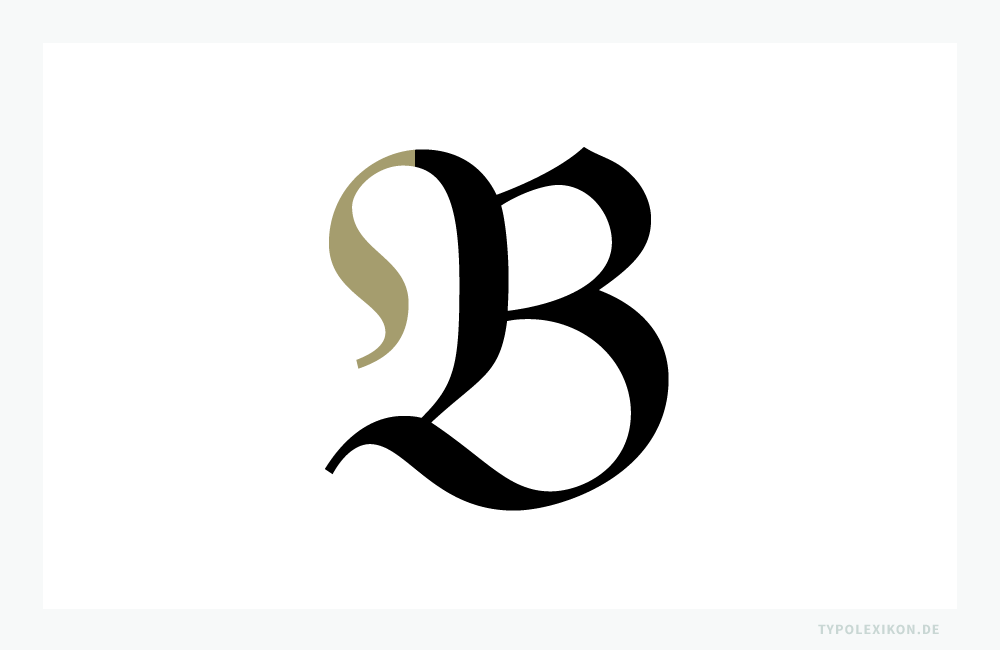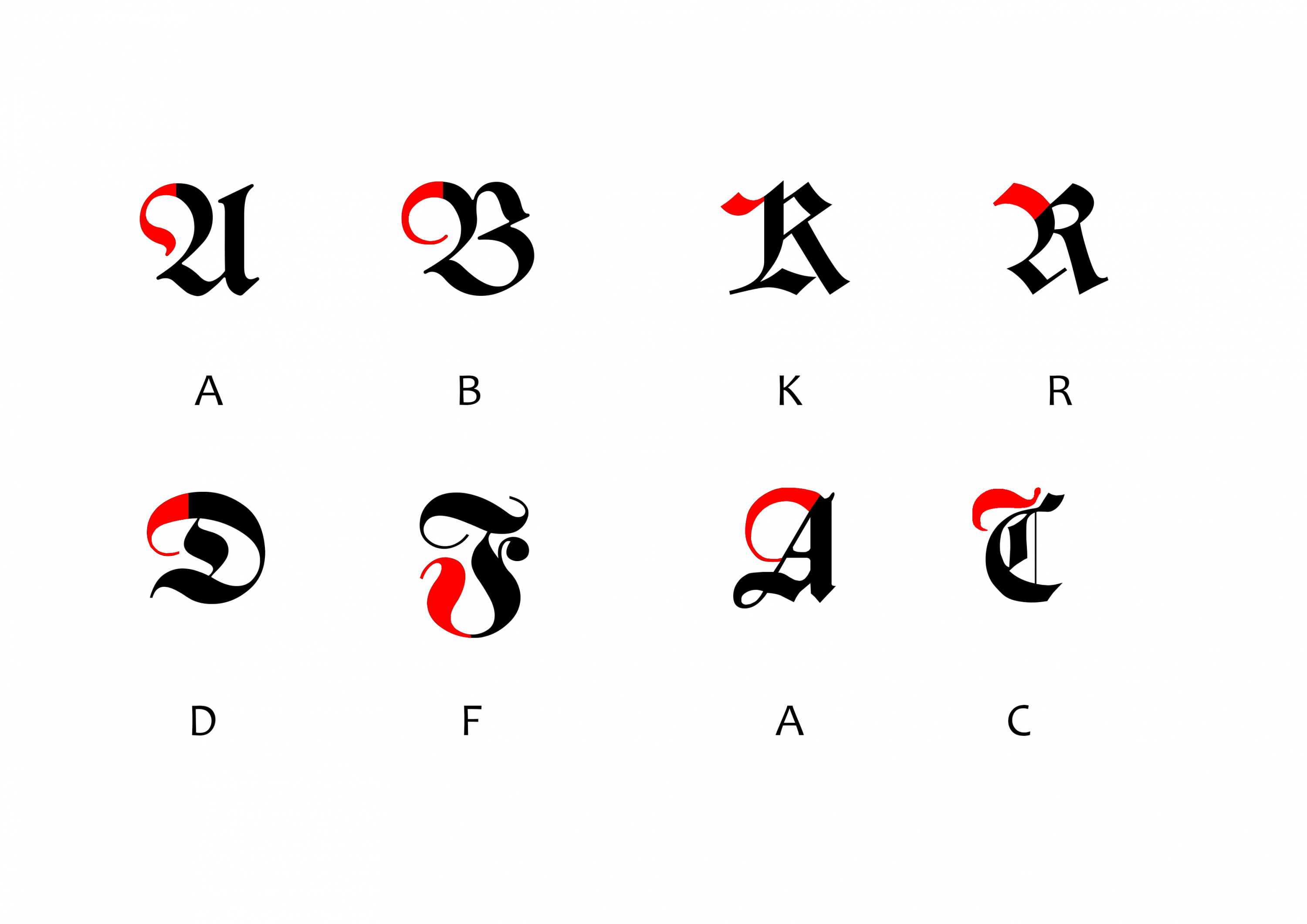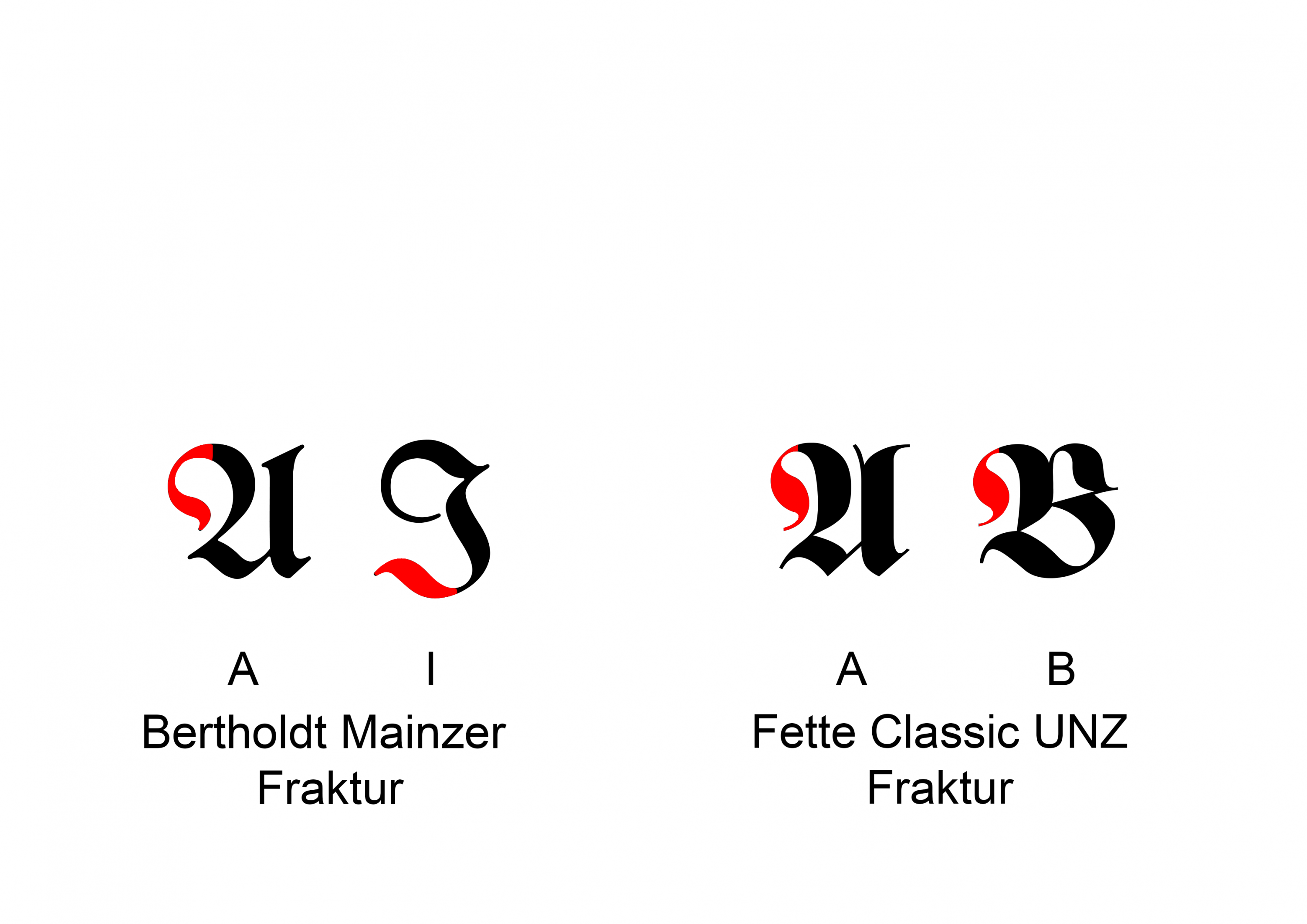
Elefantenrüssel
ich hab gerade eine Datei erstellt.
Das rot markierte soll der sogenannte Elefantenrüssel sein, habe ich das so richtig markiert?
Ich kenn das als S-förmigen Aufschwung, müsste dann beispielsweise beim B also so aussehen, bei den anderen analog:
Meiner bescheidenen Meinung nach ja. Vielleicht kann das jemand mit mehr Erfahrung bei gebrochenen Schriften bestätigen oder widerlegen :-) …